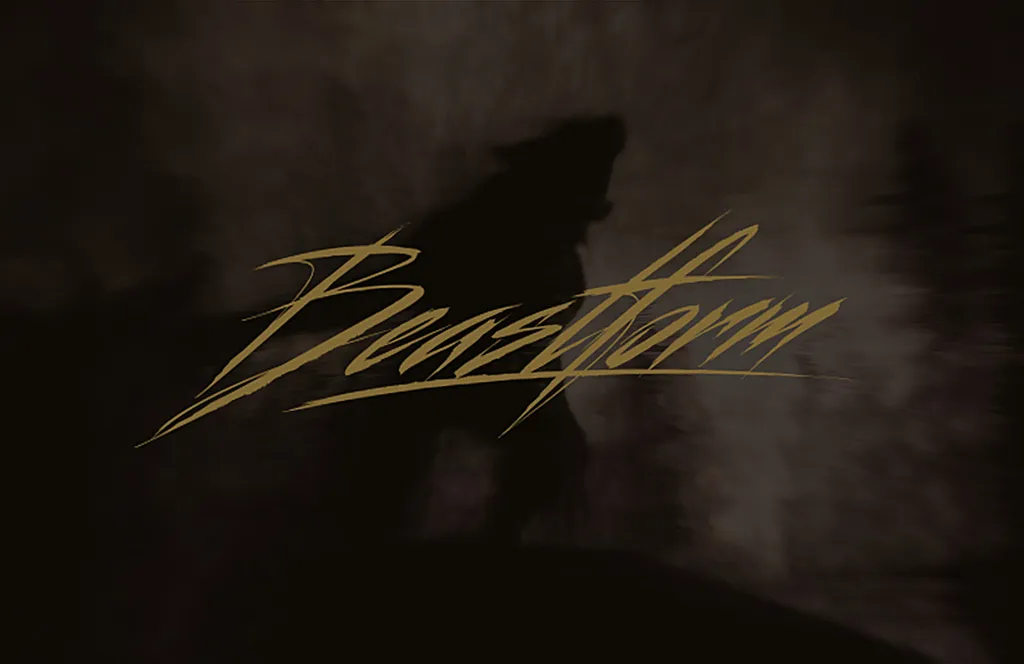
A fonte Beastform Font é uma elegante escolha para designers que valorizam uma mistura única entre a fluidez natural das letras cursivas e as linhas firmes. Com sua tipografia desenhada pelo designer Hamilton, ela oferece um toque de brilho à qualquer projeto pessoal ou mesmo iniciando os primeiros passos no campo da design gráfico para o uso comercial. A fonte Beastform Font está disponível gratuitamente para uso pessoal, mas para aplicação em trabalhos comerciais é necessário entrar em contato diretamente com Hamilton através do email . Este requisito não diminui a qualidade impressionante e versátil dessa fonte; ao contrário, adiciona um toque de personalização e exclusividade aos seus projetos.